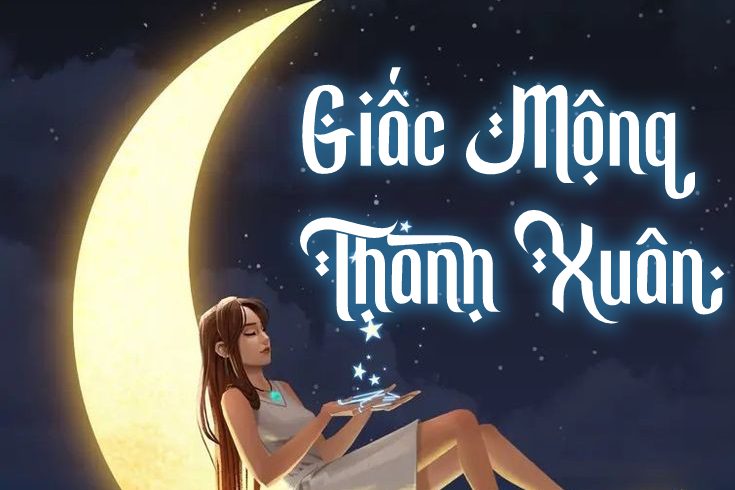
Font việt hoá MJ Ramadhan Mubarok
Tải Font việt hoá MJ Ramadhan Mubarok Miễn Phí Cho Thiết Kế Ấn Tượng
Giới thiệu về Font việt hoá MJ Ramadhan Mubarok
Trong thế giới đồ họa hiện đại, việc tìm kiếm một bộ Font Miễn Phí chất lượng để phục vụ các dự án tâm linh và lễ hội là vô cùng quan trọng. Font việt hoá MJ Ramadhan Mubarok là một lựa chọn tuyệt vời dành cho các bạn học sinh và giáo viên khi muốn trang trí bảng tin hoặc làm bài thuyết trình. Đây là kiểu chữ mang đậm phong cách Ả Rập, giúp mang lại hơi thở văn hóa đặc trưng vào từng con chữ. Phiên bản này đã được tinh chỉnh kỹ lưỡng để hỗ trợ đầy đủ bộ gõ tiếng Việt, giúp bạn dễ dàng soạn thảo nội dung mà không lo bị lỗi hiển thị hay mất nét.
Đặc điểm nổi bật của bộ chữ MJ Ramadhan Mubarok
Phong cách thiết kế độc đáo
Bộ font này sở hữu những đường nét uốn lượn khéo léo, mô phỏng lối viết thư pháp Trung Đông nhưng vẫn giữ được sự thanh thoát, hiện đại. Các ký tự được chăm chút tỉ mỉ, tạo nên sự cân đối và dễ nhìn trên nhiều bề mặt khác nhau. Điều này giúp các ấn phẩm truyền thông trở nên chuyên nghiệp và thu hút hơn trong mắt người xem.
Tính ứng dụng cao trong học tập
Với Font việt hoá MJ Ramadhan Mubarok, các bạn có thể sáng tạo thiệp chúc mừng, thiết kế tiêu đề bài học hoặc làm poster cho các sự kiện văn hóa tại trường. Kiểu chữ này không chỉ đẹp mà còn truyền tải được tinh thần đoàn kết và sự trang trọng của những dịp lễ hội lớn, giúp bài làm thêm phần sinh động.